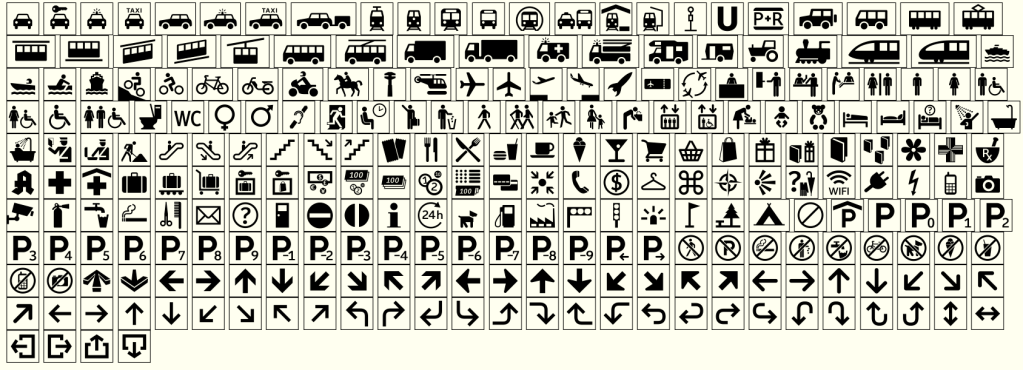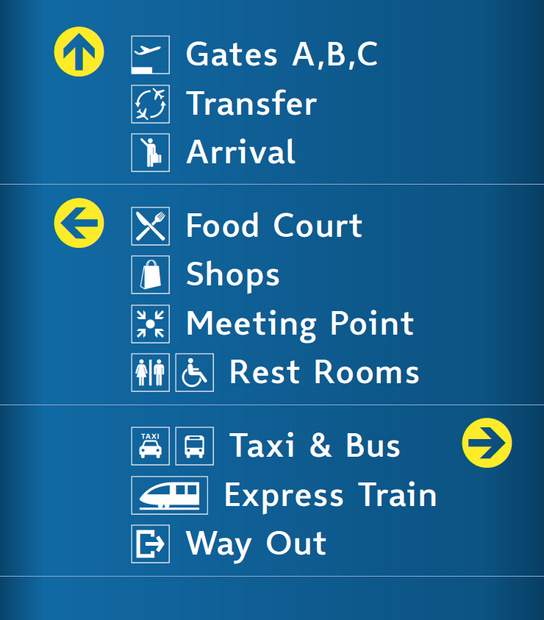
Getrennte Rolltreppen findet man auch auf Flughäfen und Bahnhöfen manchmal. In Hamburg hat man bei S-Bahn-Steigen gerne mal das Phänomen, dass die Rolltreppen sich an den entgegengesetzten Enden des Steigs befinden. Da ist ein Hinweis, wo es nach oben geht und wo nach unten (zum Beispiel zu tiefer gelegenen Tunneln) manchmal sehr angebracht und hilfreich.
Das rechte darf natürlich auch in keiner Pictosammlung fehlen:
Wie testet man denn Piktogramme, außer sie in die freie Wildbahn zu verfrachten ...? Ich könnt höchstens mal kucken, ob mir bei irgendeinem Piktogramm spontan n Äderchen im Auge platzt ... :-?
Das rechte darf natürlich auch in keiner Pictosammlung fehlen:
Warum nur habe ich den Verdacht, daß Du das nicht ironisch meinst?
Hast mich neugierig gemacht auf deine Antwort.
… vorab zu testen …
Mir drängt sich immer noch der Eindruck auf, der Arrivant reckt den Arm zum deutschen Gruße. Ich persönlich würde ihn etwas abwinkeln …
Mhh, Mist, jetzt wo es einmal gesagt ist, werd ich es nie wieder anders sehen können.
(Übrigens ein unverändert übernommenes AIGA-Symbol)
Ralf hat sich das Design ja nicht ausgedacht; es stammt, wie mehrere andere auch, von hier [Einschub: wie Ralf selbst gerade geschrieben hat]. Es ist sicher nicht verkehrt, die unverändert zu übernehmen – für den, der sich an den AIGA-Empfehlungen orientieren möchte.
Allerdings muss man schon sagen, dass das noch lange nicht heißt, dass diese Symbole in der nordamerikanischen Praxis auch verwendet werden. Ich bin ja nun überwiegend in amerikanischen Flughäfen, Bahnhöfen und ÖPNV-Systemen unterwegs, habe aber viele der empfohlenen Symbole noch nie in Anwendung gesehen. So hätte ich 41_arrivingflights_thumb.gif nie und nimmer mit »Arriving Flights« in Verbindung gebracht, sondern auch an einen Taxi-Stand gedacht. 48_exit_thumb.gif kennt in Amerika auch kein Mensch und dass es »Exit« bedeuten soll, würde erst recht niemand vermuten.
48_exit_thumb.gif kennt in Amerika auch kein Mensch und dass es »Exit« bedeuten soll, würde erst recht niemand vermuten.
Ja, das dachte ich mir schon. Siehe auch hier: http://opentype.info/blog/2010/10/27/airport-signage-and-cultural-differences/
Fällt Dir ein typischeres für Nordamerika ein? Wahrscheinlich ist schlicht der Schriftzug EXIT die verbreitete Variante, oder?
Genau. Bzw. SORTIE in Quebec.
Jetzt fällt mir übrigens ein, dass ich 48_exit_thumb.gif doch schon mal gesehen habe. Ich erinnere mich nur nicht daran, ob es in Nordamerika, Europa oder (unwahrscheinlich) noch woanders war. Das Symbol erschien über einer automatischen Schiebetür, die den Einreisebereich vom allgemeinen Terminal trennte. Ich dachte bis jetzt, es bedeutete einfach »Achtung, Schiebetür«. (Vielleicht liegt es ja daran, dass ich in meiner früheren Jugend zu viel Star Trek gesehen habe. Die dortigen Schiebetüren stecken schließlich oft in mehr oder weniger bogenförmigen Türrahmen.) :-?
Die Jungs im Hintergrund kucken auch ganz irritiert ... ;)
Wahrscheinlich ist schlicht der Schriftzug EXIT die verbreitete Variante, oder?
Ähnliches dachte ich mir auch schon zum Taxisymbol ... Die Schrift ist da so klein (und doch breiter als das Autodach) dass das eine ernsthafte Alternative wäre ...
Ohne Kontext hätte ich bei 48_exit_thumb.gif eher einen Hinweis auf einen Schlitzschraubenzieher gesehen.
Noch ein paar allgemeine Kommentare, wie meist bei mir auch wieder aus einer überwiegend nordamerikanischen Perspektive …
Zur Orientierung der Treppen und Rolltreppen: Viele Flughafenterminals und Bahnhöfe sind so angelegt, dass man durch einen Tunnel oder Gang senkrecht auf eine Halle zukommt, in der dann rechts und links Treppen oder Rolltreppen abgehen. Die Orientierung der Treppen auf den Symbolen stimmt dann oft mit den realen Treppen überein. Ich würde empfehlen, die entsprechenden Piktogramme auch gespiegelt anzubieten, da ist dann für jeden was dabei.
Der untere halbe Balken in den Symbolen für Abflug und Ankunft wird m.W. hier nicht oder kaum verwendet. Wie wär’s mit Alternativsymbolen, in denen er weggelassen wird?
Maulschlüssel statt Franzose (wurde schon vorgeschlagen)
Was fehlt noch?
• das 3-Balkensymbol für Rettungsdienste, als Piktogramm wahrscheinlich ohne Outline und Schlange.
• ein Kiss-and-Ride-Symbol (Irgendwo habe ich mal eins gesehen, dass klar erkennbar war, aber simpler als 90px-Marta_kiss_ride.jpg; leider habe ich es nicht archiviert. Vielleicht fällt dir ja was ein.)
Die neuen »Bitte Umkehren«-Piktogramme (vorletzte Zeile, 5. und 6. von rechts) sind übrigens wichtig; solche wollte ich gerade noch vorschlagen. In EWR ist die Wegeführung z.B. an mehreren Stellen so, dass man in 180° um eine Wand biegen muss, um dann in Gegenrichtung weiter zu laufen. Da ist es wichtig, dass der Balken mit dem Pfeil dran länger ist als der von der aktuellen Position weg führende.
was bedeutet das bett mit dem fragezeichen? bei den betten würde ich auch nochmal ran und alle gleich machen…
Lodging Info.
Die Betten sind zur alternativen Verwendung gedacht, daher müssen sie nicht gleich aussehen. Das eine ist in Deutschland üblicher, das andere in den USA. Genau wie bei den beiden Varianten für Restaurant.